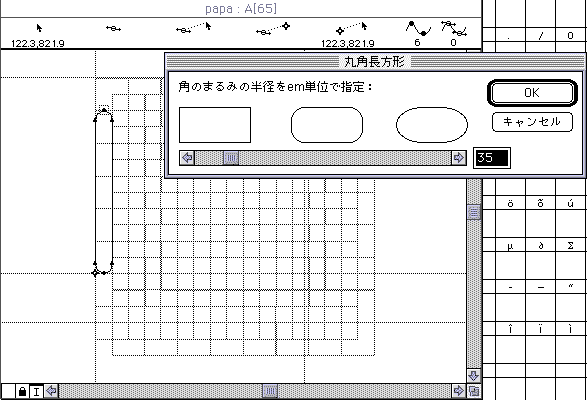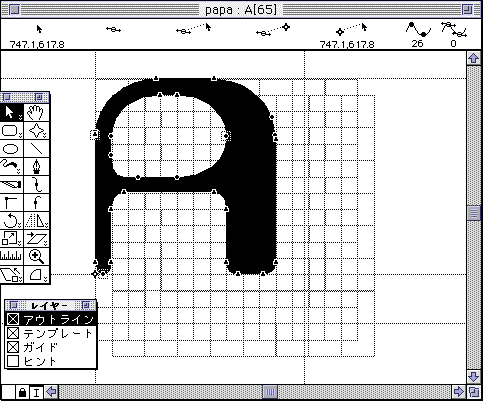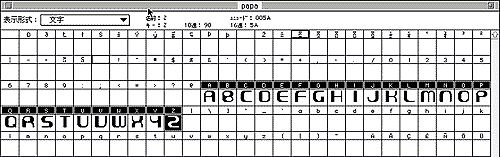
Fontgrapher
まず、フォントグラファーを起動してください!
最初はあんまり気張らずに、音楽でも聞きながら
作ってみましょう。いざ、フォントツクリの世界へ
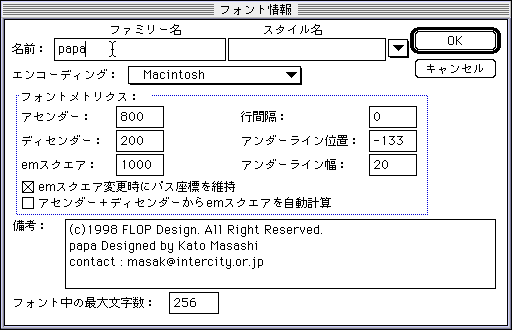
はじめに[エレメント>フォント情報]を選択しフォント名を記入。名前を決めておくと
僕はやる気が出てきます。あと備考にcopyrightや連絡先を書いて、デザイナー 気分!
フォントメトりクスの設定はこのままでも大丈夫ですが、場合によって変更したりも
できます。
なんとなく「A」から始めてみます。僕はいつもテンプレートにグリッドを使用します。
そうするとフォントの統一感がとりやすいのです。 長方形ツール棒を描いてみます。
設定で でアールの大きさを変えられるので試してみてください。
イラストレーターの要領で文字を作っていきます。ちょっとかわいらしくて
独特のアールの変化がある「A」が出来上がりました。
この調子で「A」から「Z」までを作り上げていきます。 文字を作っていく上で
同じ大きさのアールを使っていけば統一感がとりやすいはずです。
次回に続く!